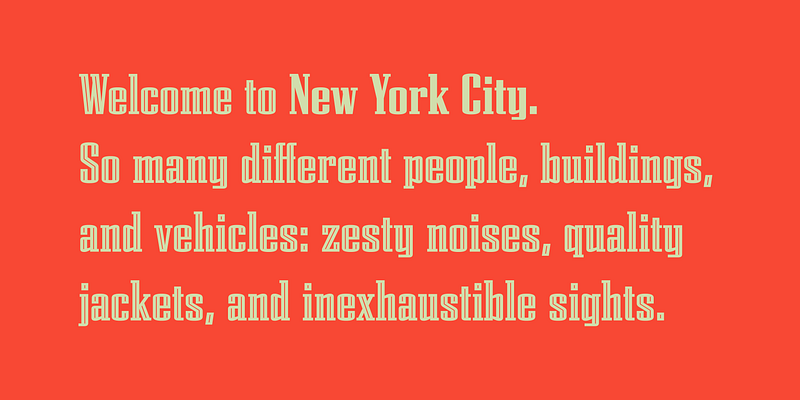
En los estilos condensados de la mayoría de las serifas geométricas, los óvalos débiles sustituyen a las poderosas formas circulares. En Citadel, Tobias Frere-Jones sigue una alternativa más fuerte, sustituyendo los lados curvos de los caracteres redondos por trazos rectos. Las curvas horizontales planas juegan con la variedad de serifas, en contrapunto con el ritmo repetitivo de las verticales. En el estilo Inline, la raya se suma a ese ritmo, creando un tipo de letra que ofrece una geometría potente y elegante.